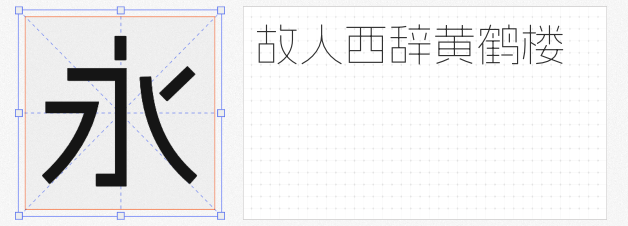
首先,不得不提的是“阿里健康体2.0”字体家族。这款字体由方正字库与阿里健康团队联合设计开发,旨在帮助1700多万视障群体安全用药。其亲和、稳重、简约的气质,体现了对特殊群体的关怀,更通过技术创新实现了汉字字符与盲文的串联,成为首款可以直接输出中文、注音文字、盲文的多功能字库。如今,阿里健康体2.0的两款字重面向全社会永久免费开放使用,希望通过技术公益推动无障碍环境建设,传递现代设计的人文关怀。
接下来是“阿里妈妈数黑体”。这款字体字型饱满、体态中正,布白极具现代韵律,落笔厚实而简练。在“图形感”和“书写感”之间找到了完美的平衡点,使其在正常阅读的同时也不乏辨识度。特殊的笔画处理更是让字体在字里行间流露出醒目、时尚和先锋的视觉感受。
最后是“阿里妈妈方圆体 VF”。这款字体包含了黑体和圆体两个字型的变轴,黑体部分同样饱满、体态中正,而圆体则更加灵动、圆润。一个字体即可覆盖多风格设计,无论是电商、广告、品牌形象还是推广物料等场景,都能轻松应对。